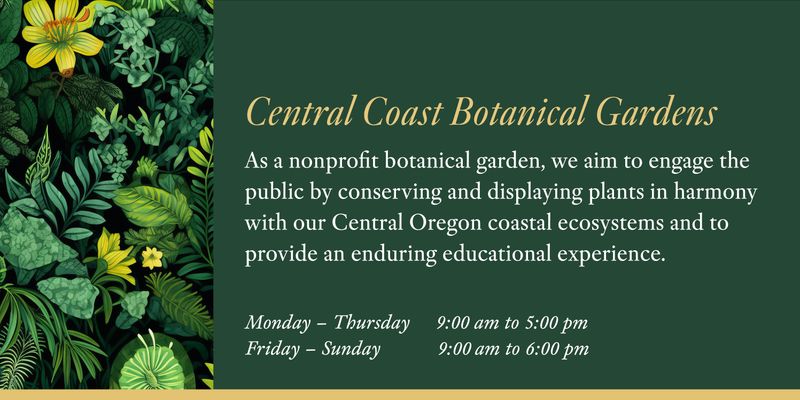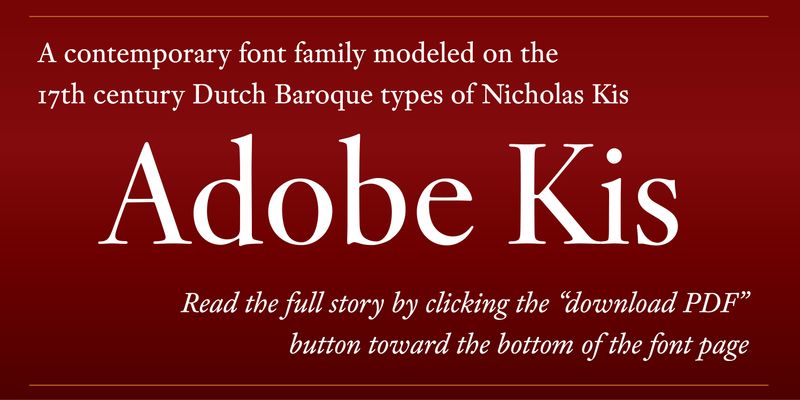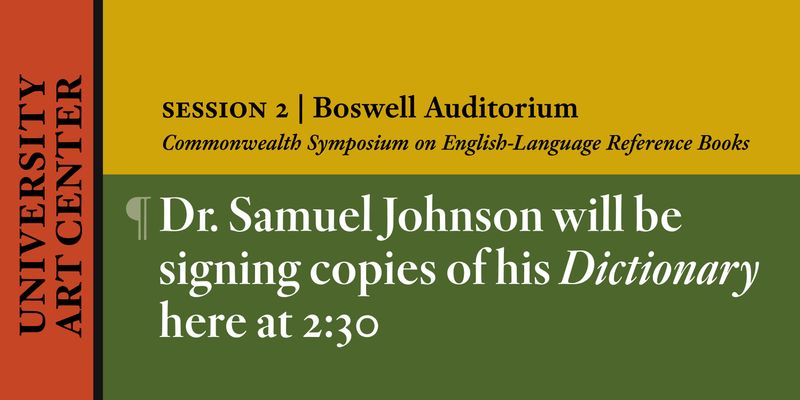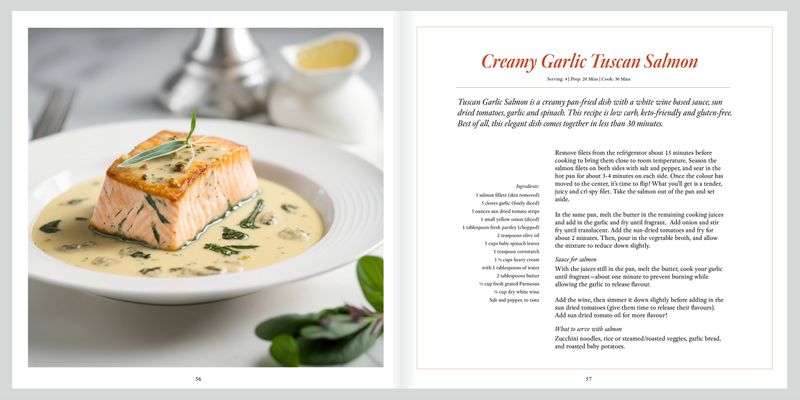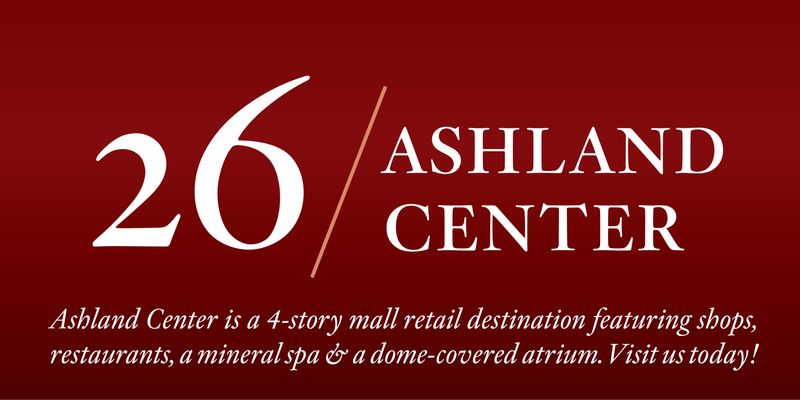
Adobe Kis(“Kish”로 발음)는 Adobe가 제공하는 고전 서적 유형의 최신 부활 버전입니다. 디자이너인 Robert Slimbach는 원본 유형의 활력과 뉘앙스를 포착하는 동시에 진화하는 디지털 매체의 요구 사항에 부합하도록 노력했습니다.
Adobe Kis는 17세기 네덜란드 활자체 스타일의 견고하고 다양한 텍스트 서체이지만 제작자인 Nicholas Kis는 헝가리인이었습니다. 소설, 역사, 대중과학, 에세이, 여행서, 요리책, 참고서 등의 도서에 사용하기에 매우 적합합니다. 보고서와 출판물 디자인 모두에 대해서도 잘 어울립니다.
Adobe Originals 프로그램은 1989년 Adobe 사내 서체 파운드리로 시작하여 모범적인 디자인 품질, 기술적 충실도 그리고 미적 영속성을 가진 오리지널 서체를 창안하기 위해서 구성되었습니다.
현재 Type 팀의 임무는 디자인과 기술의 가능성을 모색하는 정교하고 심지어 실험적일 수도 있는 서체를 만드는 것입니다. Adobe Originals로 출시된 서체는 수년간의 작업 및 연구의 결과로서 그 개발의 야심과 품질이라는 점에서 업계의 표준으로 인정되고 있습니다.